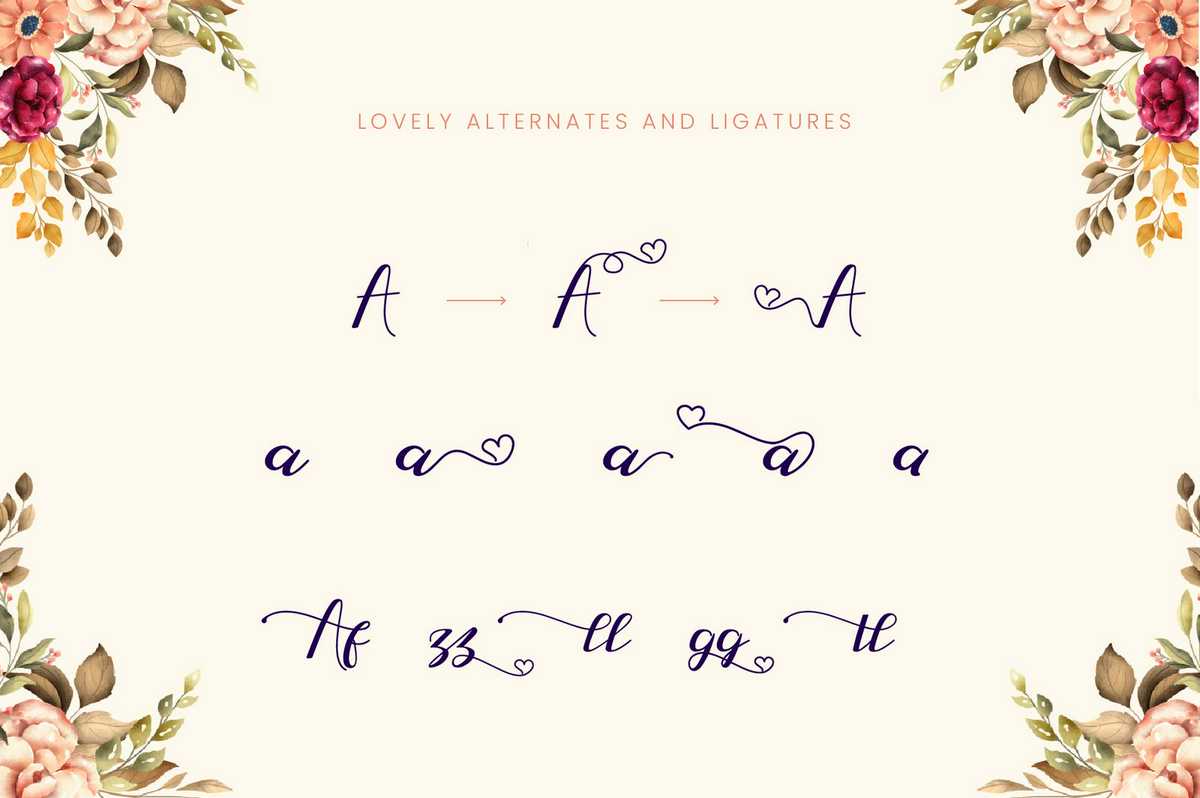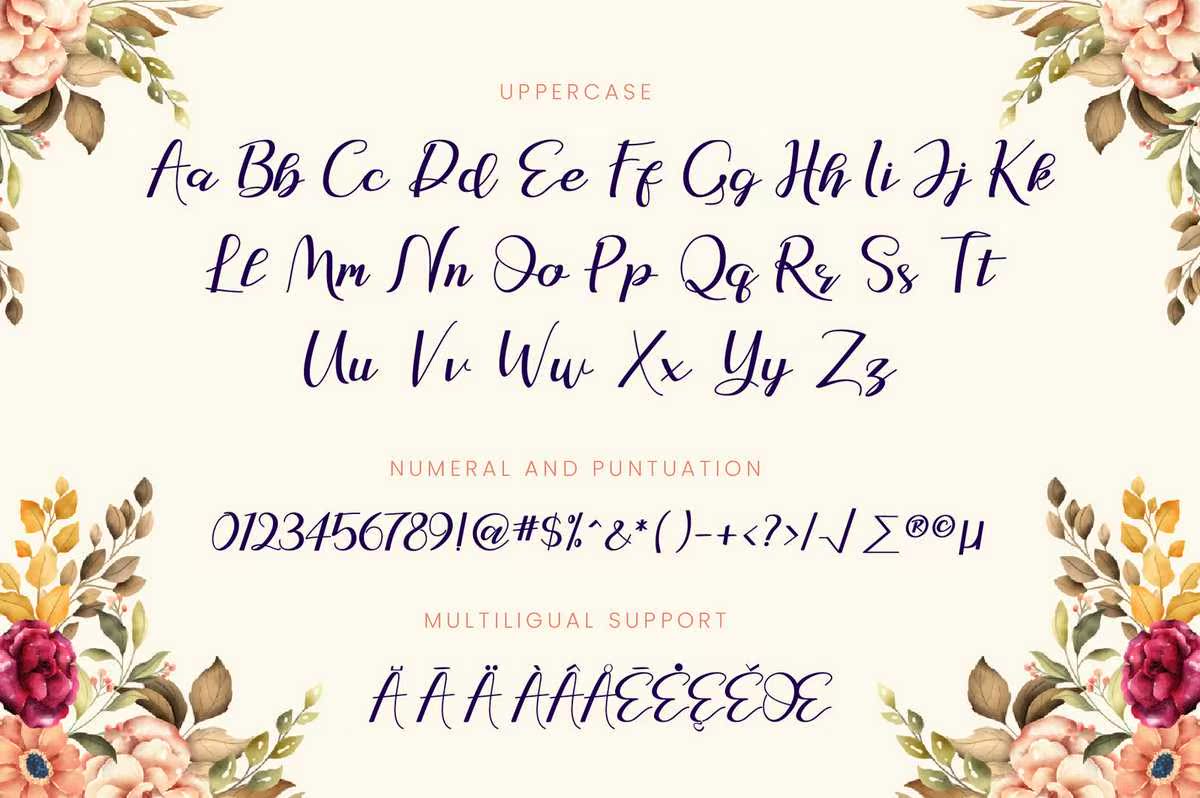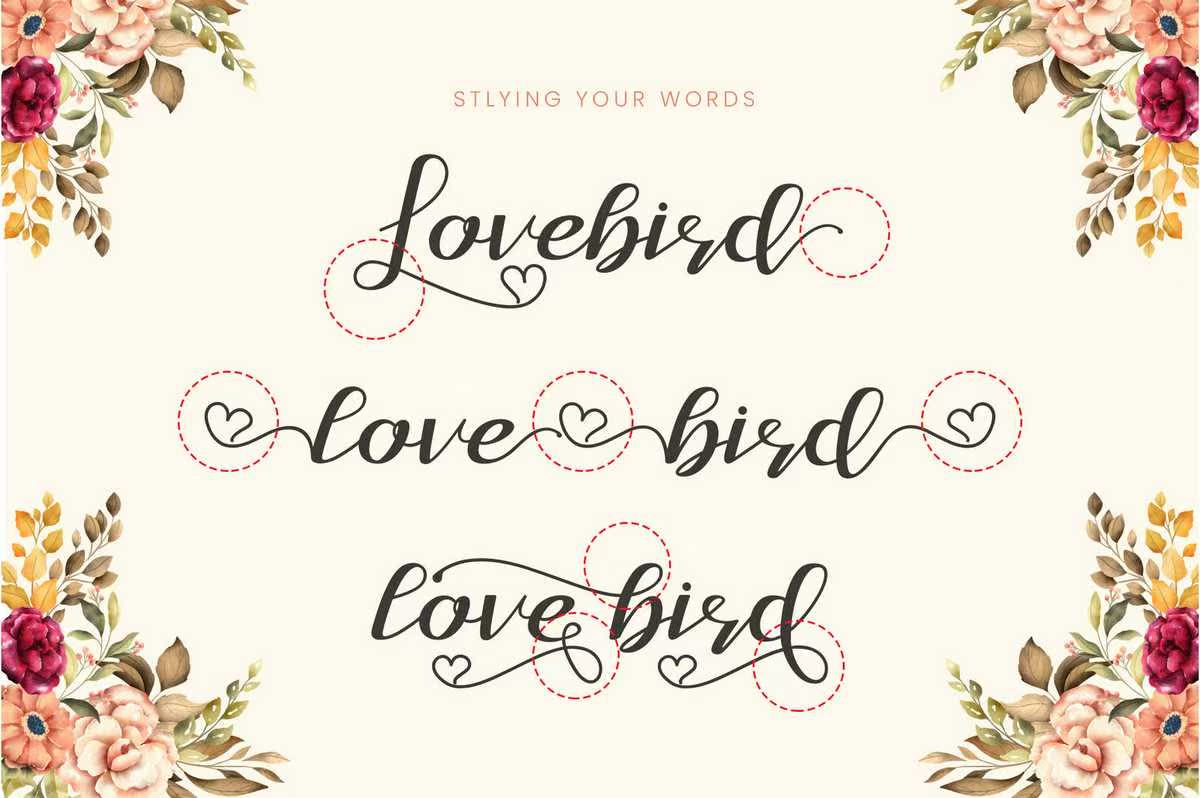
Lovelynatasy是一款专为支持您的精彩项目而设计的LegantScriptFontWeed。Lovelynatasy是品牌项目、徽标、婚礼设计、社交媒体、广告、产品包装、产品设计、标签、照片、水印、邀请函、文具、,以及任何需要精美手工制作的项目。Lovelynata是一个LegantScriptFontWedesigned以支持您的精彩项目。Lovelynata是品牌项目、徽标、婚礼设计、社交媒体、广告、产品包装、产品设计、标签、摄影、水印、邀请函、文具、,以及任何需要手工制作的项目。